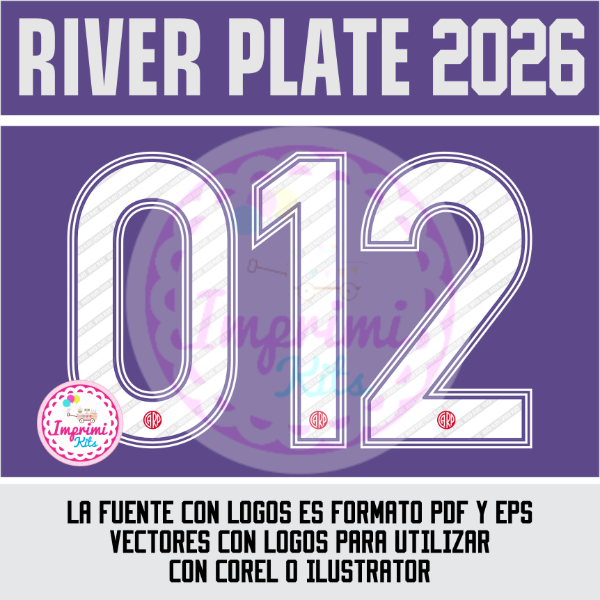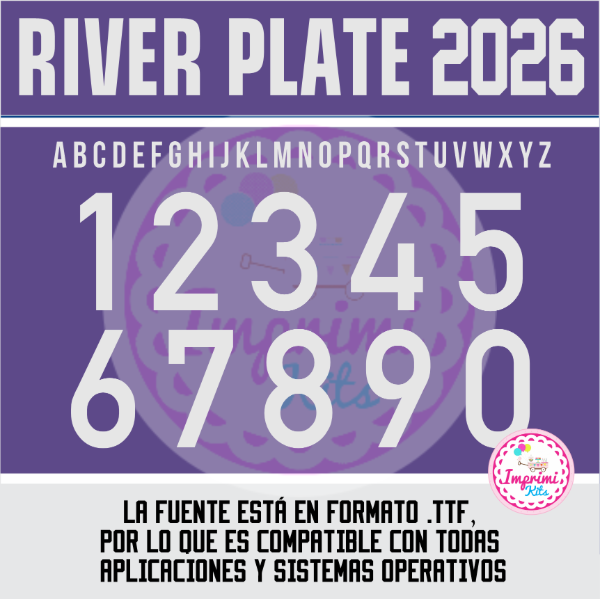
Tipografia River 2026 Tercera Equipación Camiseta Ttf Numeros Dorsal DTF
Tipografía Números Fuente
Los vectores de numeros dorsales incluyen detalles y el logo oficial en el numero (VER FOTO 2)
Realizá todo tipo de creaciones con la tipografía utilizada actualmente en el club